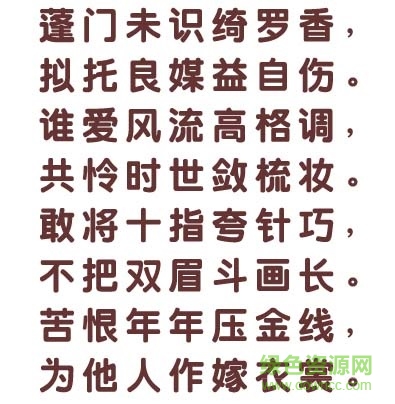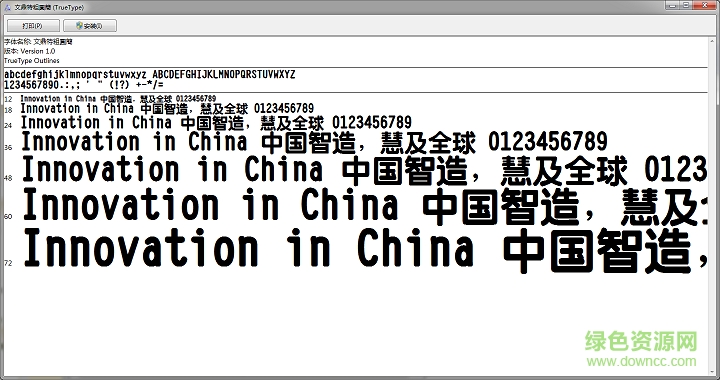
文鼎特粗圓簡(jiǎn)字體是一款筆畫特別粗的簡(jiǎn)體字體。該字體整體效果成方正,但是拐角處都是圓弧形,渾厚中帶有點(diǎn)圓潤(rùn),感興趣的用戶們可別錯(cuò)過了,歡迎來綠色資源網(wǎng)下載使用哦。
文鼎特粗圓簡(jiǎn)是款應(yīng)用于設(shè)計(jì)方面的黑體字體,該字體線條非常的粗壯,字形端正大方得體,整體效果非常的出色,且字庫(kù)完整,可以廣泛應(yīng)用于廣告設(shè)計(jì)等方面。